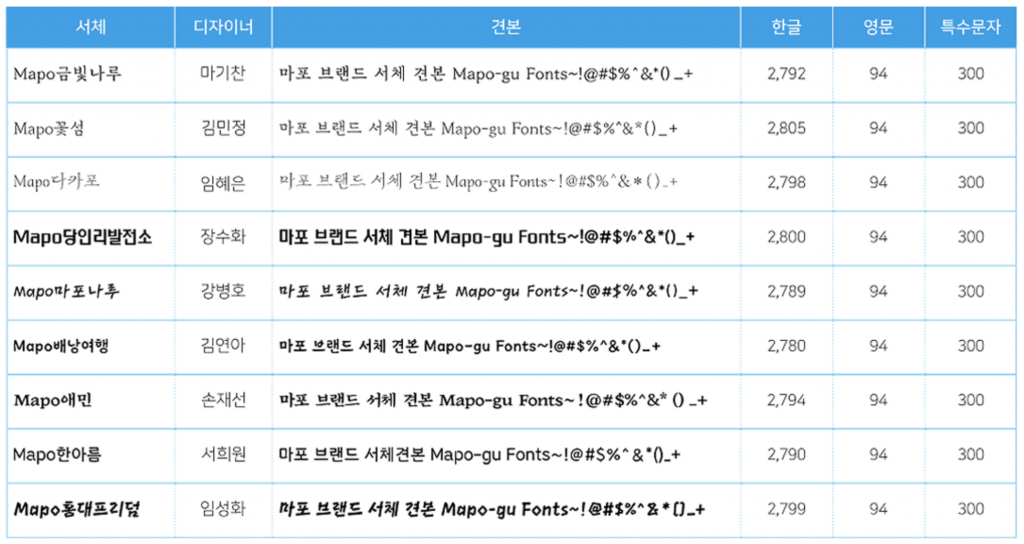
마포구, 청년들과 함께 제작한 9종의 무료폰트 공개
마포구청이 청년들과 함께 만든 무료폰트를 공개했다. 각 폰트는 홍대 문화(홍대프리덤), 자생하는 난지도(꽃섬), 역사와 문화(금빛나루), 마포나루 새우젓축제(마포나루), 클래식 음악 축제(다카포) 양화진 외국인 선교사묘원(애민), 당인리발전소(당인리발전소), 개방과 소통(한아름), 자유(배낭여행)를 상징한다.
특이한 점은 다른 지자체에서 만든 무료폰트와 다르게 청년 일자리 창출과 연결지었다는 점이다. ‘서울형 뉴딜 일자리 사업’의 일환으로 디자인・컴퓨터 전공 미취업 청년을 선발해 약 11개월 간 급여 및 교육 프로그램을 제공하면서 서체를 개발토록 지원했다. 이렇게 프로젝트에 참여한 학생들은 각각 유명 폰트회사에 입사하거나 ‘한글 글꼴 디자인공모전’에서 수상하는 등 나름의 성과도 거뒀다.